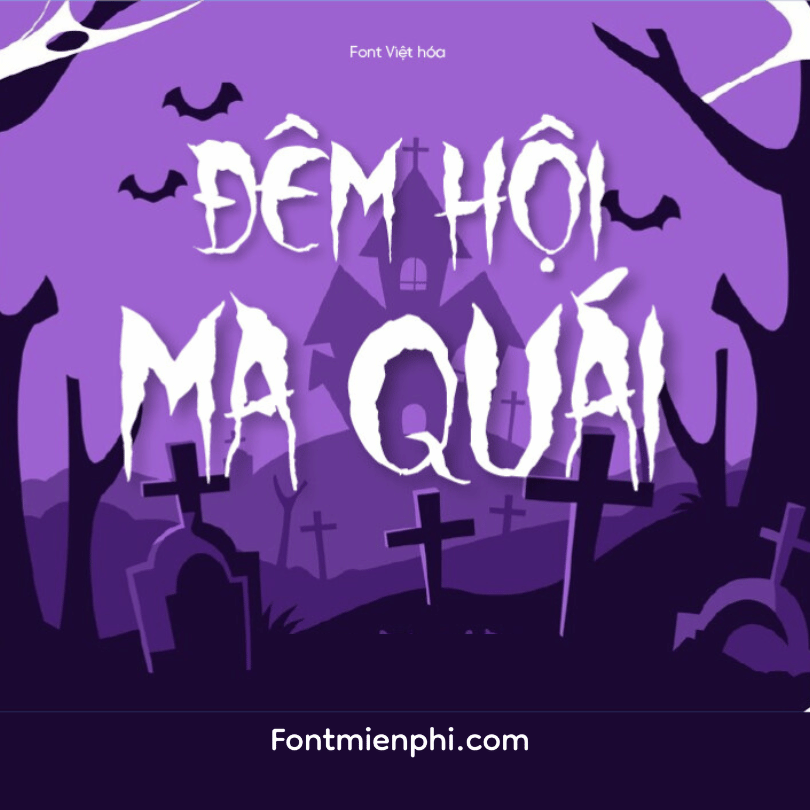
Font Việt hóa 1FTV VIP Wolf Moon ,Font Halloween
Font Việt hóa 1FTV VIP Wolf Moon ,font Halloween – Phông Chữ Halloween Huyền Bí Đậm Chất Lang Trăng
1FTV VIP Wolf Moon là font chữ Việt hóa cao cấp lấy cảm hứng từ những đêm trăng sói đầy ma mị. Với nét chữ sắc sảo như vết cào của nanh vuốt kết hợp hiệu ứng ánh trăng bạc, font chữ này sẽ đem đến không khí Halloween vừa hoang dã vừa quyến rũ.
ĐẶC ĐIỂM NỔI BẬT:
✔ Phong cách “lang trăng” đậm chất Gothic – nét chữ mảnh mai như vết cào kết hợp hiệu ứng bóng đổ hình sói
✔ Bộ ký tự đặc biệt – bao gồm 20+ glyph hình mặt trăng, dấu chân sói và biểu tượng huyền bí
ỨNG DỤNG SÁNG TẠO:
• Thiết kế poster phim ma sói, truyện kinh dị
• Bìa album nhạc Gothic, Metal
• Logo quán café theme hoang dã
• Thiệp mời tiệc Halloween đẳng cấp